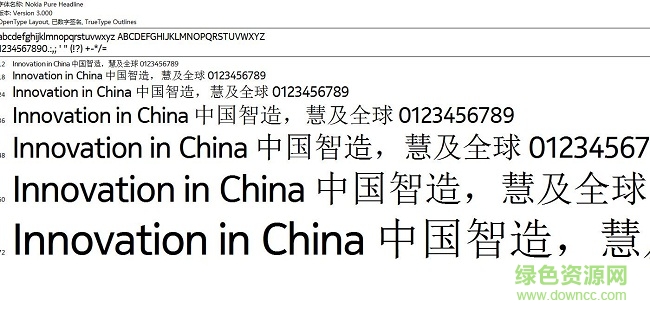
nokia pure.ttf字體是諾基亞手機(jī)的默認(rèn)系統(tǒng)字體,屬于無(wú)襯線字體類,干凈大氣辨識(shí)度出色,用在顯示器上的效果比較賞心悅目,喜歡的朋友快來(lái)下載吧!
該字體由Dalton Maag設(shè)計(jì),主打簡(jiǎn)約、自然、純粹?;蛟S在普通大眾看來(lái)就是一個(gè)極為普通的電腦化英文字形!
襯線指的是字母結(jié)構(gòu)筆畫之外的裝飾性筆畫,沒(méi)有襯線的字體,則叫做無(wú)襯線體(sans-serif),凡是使用無(wú)襯線字體的,必須保證其在正文內(nèi)容中的可讀性。